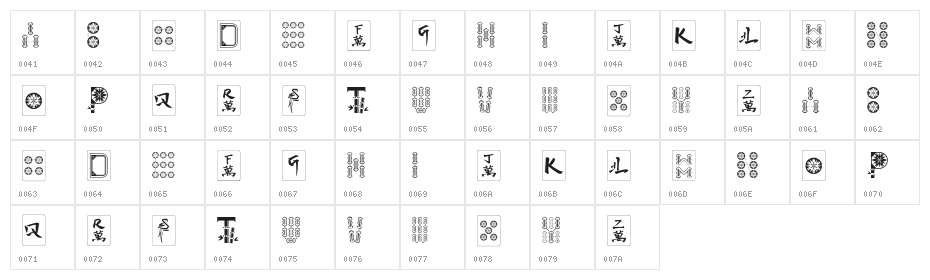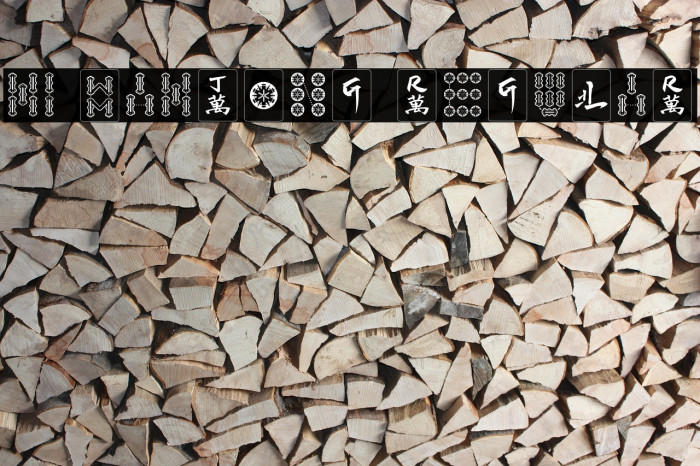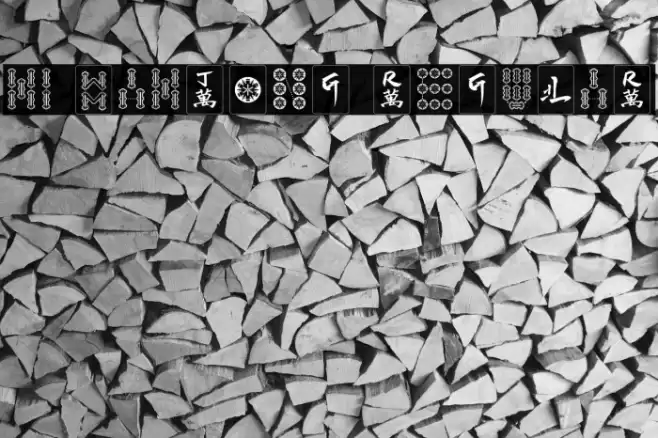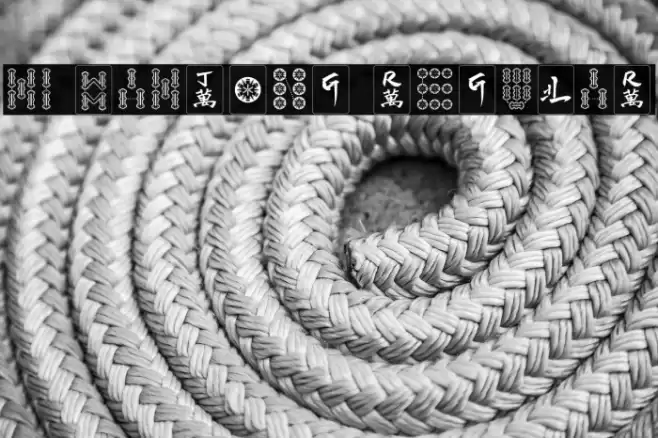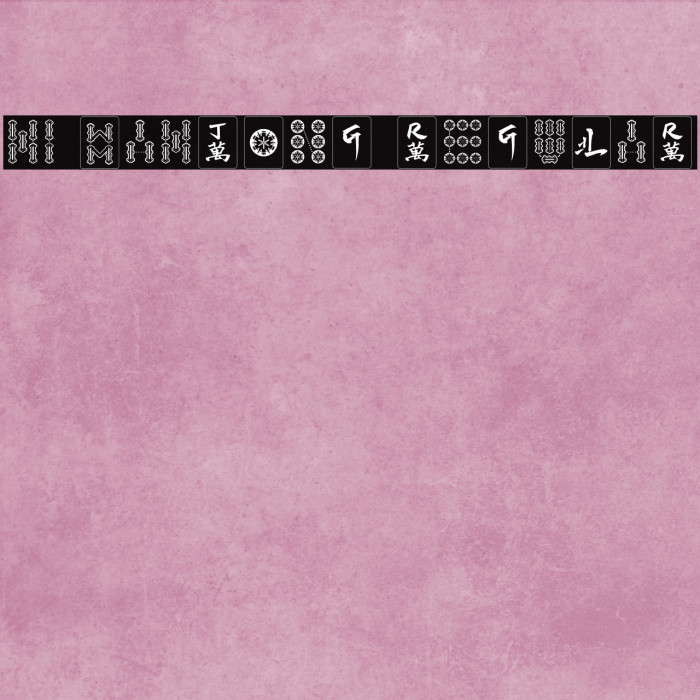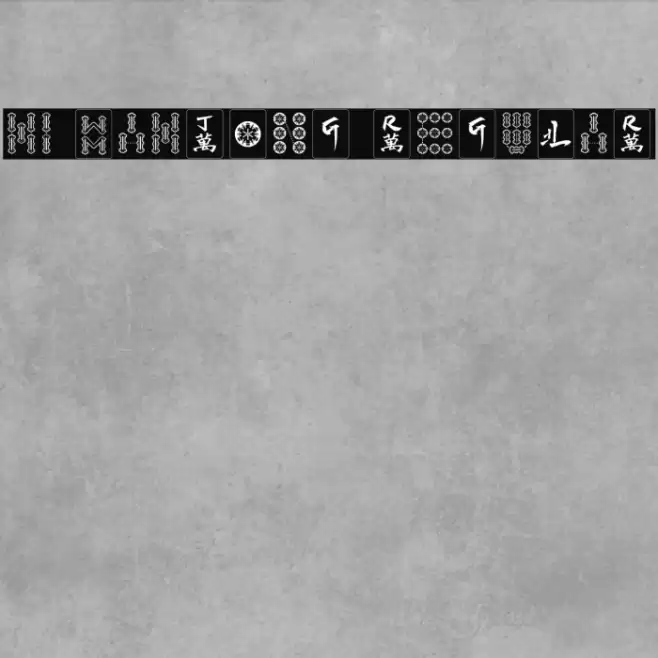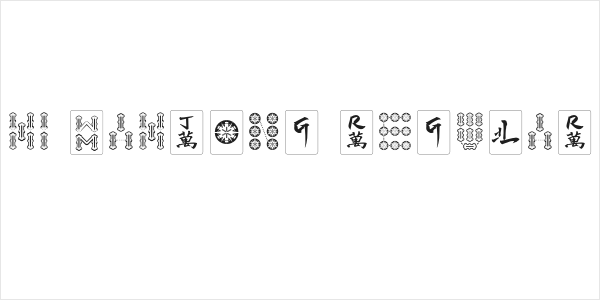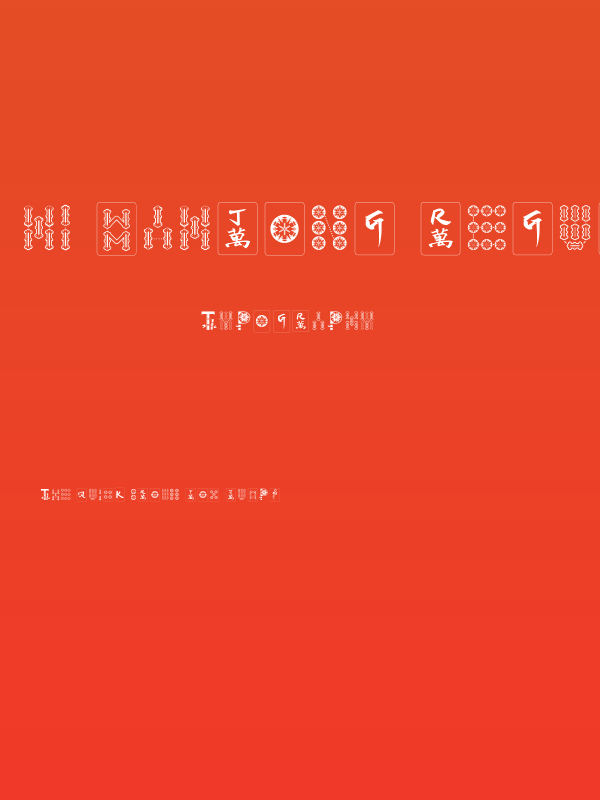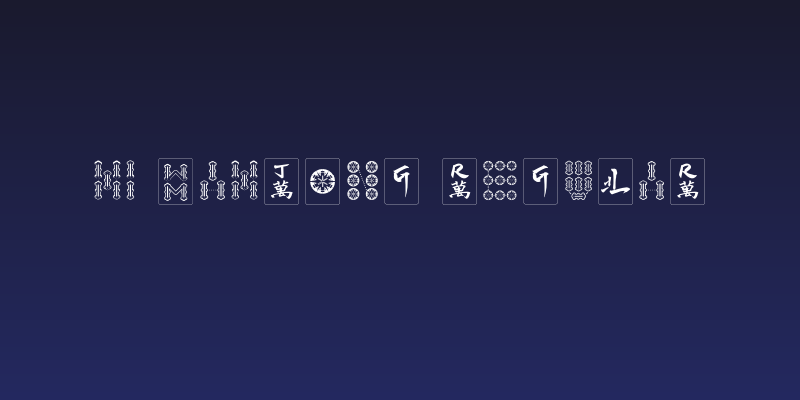
Hi Mahjong Regular Font
Fonts by Kaman L
| 用途 | Logos, Posters, Artistic projects |
| おすすめプロジェクト | Ideal for cultural event posters, themed invitations, board game designs, and artistic projects requiring a traditional touch. |